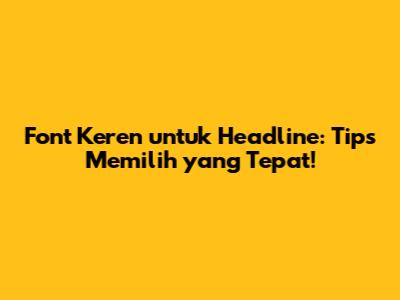
- Ukuran font: Pastikan ukuran font cukup besar agar mudah dibaca, terutama di layar kecil seperti smartphone. Ukuran font minimal untuk headline biasanya sekitar 24pt.
- Spasi antar huruf dan baris: Spasi yang cukup akan membuat huruf dan baris tidak terlalu berdekatan, sehingga lebih mudah dibaca. Hindari menggunakan spasi yang terlalu rapat atau terlalu lebar.
- Kontras warna: Pastikan ada kontras yang cukup antara warna font dan background. Hindari menggunakan warna yang terlalu mirip atau terlalu terang, karena bisa membuat mata lelah.
- Jenis font: Pilih jenis font yang memiliki desain karakter yang jelas dan mudah dikenali. Hindari menggunakan font yang terlalu rumit atau terlalu banyak ornamen.
- Kontras: Pilih font yang memiliki kontras yang cukup satu sama lain. Misalnya, kamu bisa mengombinasikan font serif untuk headline dengan font sans-serif untuk body text, atau sebaliknya.
- Hierarki: Gunakan font yang lebih tebal atau lebih besar untuk headline, dan font yang lebih tipis atau lebih kecil untuk body text. Ini akan membantu menciptakan hierarki visual yang jelas dan memudahkan pembaca untuk membedakan antara headline dan isi artikel.
- Kesesuaian: Pastikan font yang kamu pilih memiliki gaya dan tone yang serupa. Hindari mengombinasikan font yang terlalu berbeda, karena bisa terlihat aneh dan tidak profesional.
- Serif: Times New Roman, Georgia, Garamond, Didot
- Sans-serif: Arial, Helvetica, Open Sans, Roboto, Lato, Montserrat, Bebas Neue
- Display: Impact, Anton, Oswald, Playfair Display, Lobster
- Gunakan keyword di headline: Ini akan membantu meningkatkan SEO dan membuat headline-mu lebih relevan dengan pencarian pengguna.
- Buat headline yang menarik dan provokatif: Headline yang membangkitkan rasa ingin tahu akan membuat orang lebih tertarik untuk membaca kontenmu.
- Uji coba berbagai headline: Coba buat beberapa versi headline yang berbeda, lalu lihat mana yang paling efektif menarik perhatian pembaca.
Memilih font yang cocok untuk headline itu krusial, guys! Headline adalah wajah dari kontenmu, kesan pertama yang menentukan apakah orang tertarik untuk membaca lebih lanjut atau langsung scroll lewat. Bayangin deh, udah capek-capek bikin artikel super keren, tapi headlinenya pakai font yang bland dan nggak menarik? Sayang banget, kan! Nah, di artikel ini, kita bakal kupas tuntas gimana caranya memilih font yang bikin headline-mu stand out dan sukses mencuri perhatian.
Mengapa Pemilihan Font Headline itu Penting?
Font bukan sekadar hiasan, guys. Lebih dari itu, font adalah voice visual dari brand dan kontenmu. Pemilihan font yang cocok untuk headline bisa memengaruhi persepsi pembaca tentang kredibilitas, profesionalisme, dan bahkan emosi yang ingin kamu sampaikan. Bayangin, headline berita keuangan pakai font Comic Sans? Nggak banget, kan! Sebaliknya, headline artikel tentang desain grafis dengan font futuristik dan edgy bisa langsung menarik perhatian para desainer.
Selain itu, font yang cocok untuk headline juga berperan penting dalam readability atau keterbacaan. Headline yang mudah dibaca akan membuat pembaca lebih cepat memahami inti dari kontenmu. Ini penting banget di era digital yang serba cepat ini, di mana orang cenderung hanya scan informasi sebelum memutuskan untuk membaca lebih detail. Kalau headlinenya aja udah bikin mata lelah, bisa-bisa mereka langsung kabur!
Nggak cuma itu, font yang cocok untuk headline juga membantu membangun brand recognition. Dengan menggunakan font yang konsisten untuk headline di semua platform, kamu bisa menciptakan identitas visual yang kuat dan mudah diingat oleh audiensmu. Jadi, setiap kali mereka lihat font itu, mereka langsung ingat sama brand atau kontenmu. Keren, kan?
Memilih font yang tepat adalah investasi untuk kesuksesan kontenmu. Jangan anggap remeh hal ini, ya! Dengan pemilihan font yang cermat, kamu bisa meningkatkan engagement, membangun brand awareness, dan pada akhirnya, mencapai tujuan kontenmu.
Faktor-Faktor yang Perlu Dipertimbangkan dalam Memilih Font Headline
Oke, sekarang kita masuk ke bagian yang lebih teknis, yaitu faktor-faktor yang perlu kamu pertimbangkan saat memilih font yang cocok untuk headline. Jangan khawatir, nggak serumit yang kamu bayangkan kok!
1. Tujuan dan Target Audiens
Sebelum memilih font, kamu harus tahu dulu apa tujuan dari headline-mu dan siapa target audiensmu. Apakah kamu ingin menyampaikan informasi yang serius dan formal, atau justru ingin mengajak pembaca untuk bersantai dan menikmati konten yang ringan? Apakah target audiensmu adalah profesional muda yang tech-savvy, atau ibu-ibu rumah tangga yang mencari tips praktis? Jawaban dari pertanyaan-pertanyaan ini akan sangat memengaruhi pilihan fontmu.
Misalnya, kalau kamu menulis artikel tentang investasi saham untuk pemula, kamu mungkin ingin menggunakan font yang clean, profesional, dan mudah dibaca, seperti Arial, Helvetica, atau Open Sans. Font-font ini memberikan kesan kredibel dan terpercaya, yang penting banget dalam dunia keuangan. Sebaliknya, kalau kamu menulis artikel tentang fashion trends untuk remaja, kamu bisa lebih berani bereksperimen dengan font yang lebih stylish, playful, dan trendy, seperti Bebas Neue, Montserrat, atau Raleway.
Ingat, font adalah alat untuk berkomunikasi. Pilihlah font yang paling efektif untuk menyampaikan pesanmu kepada target audiensmu.
2. Gaya dan Tone Konten
Selain tujuan dan target audiens, kamu juga perlu mempertimbangkan gaya dan tone kontenmu. Apakah kontenmu bersifat formal atau informal? Serius atau lucu? Klasik atau modern? Pilihan fontmu harus selaras dengan gaya dan tone kontenmu.
Misalnya, kalau kamu menulis artikel tentang sejarah kuno, kamu mungkin ingin menggunakan font yang klasik dan elegan, seperti Times New Roman, Garamond, atau Didot. Font-font ini memberikan kesan vintage dan berwibawa, yang cocok banget untuk topik sejarah. Sebaliknya, kalau kamu menulis artikel tentang startup teknologi, kamu bisa menggunakan font yang modern dan futuristik, seperti Roboto, Lato, atau SF Pro Display.
Konsistensi adalah kunci. Pastikan font yang kamu pilih konsisten dengan gaya dan tone kontenmu di seluruh platform. Ini akan membantu membangun identitas visual yang kuat dan mudah diingat.
3. Readability dan Legibility
Ini adalah faktor yang paling penting, guys! Font yang cocok untuk headline harus mudah dibaca (readability) dan mudah dikenali setiap karakternya (legibility). Percuma kalau fontnya keren banget, tapi susah dibaca, kan? Pembaca bisa frustrasi dan akhirnya malah nggak jadi baca kontenmu.
Untuk memastikan readability dan legibility yang baik, perhatikan hal-hal berikut:
Uji coba adalah segalanya. Coba cetak headline-mu dalam berbagai ukuran dan warna, lalu minta teman atau kolega untuk membacanya. Perhatikan apakah mereka kesulitan membaca atau mengenali huruf-hurufnya. Jika ya, berarti kamu perlu mencari font lain.
4. Ketersediaan dan Kompatibilitas
Pastikan font yang kamu pilih tersedia dan kompatibel di semua platform yang kamu gunakan, baik website, media sosial, maupun email. Beberapa font mungkin hanya tersedia untuk penggunaan komersial, jadi pastikan kamu memiliki lisensi yang sesuai. Selain itu, beberapa font mungkin tidak didukung oleh browser atau sistem operasi tertentu, sehingga bisa tampil berbeda atau bahkan tidak tampil sama sekali di perangkat yang berbeda.
Untuk menghindari masalah ini, kamu bisa menggunakan font yang web-safe, yaitu font yang sudah terpasang secara default di sebagian besar sistem operasi, seperti Arial, Helvetica, Times New Roman, Georgia, dan Verdana. Atau, kamu bisa menggunakan layanan web font seperti Google Fonts atau Adobe Fonts, yang menyediakan ribuan font gratis dan berbayar yang bisa kamu gunakan di website-mu.
Periksa lisensi dengan cermat. Pastikan kamu memiliki hak untuk menggunakan font yang kamu pilih, terutama jika kamu menggunakannya untuk tujuan komersial.
5. Kombinasi Font
Seringkali, headline akan terlihat lebih menarik jika dikombinasikan dengan font lain untuk body text. Namun, memilih kombinasi font yang tepat bisa jadi tricky. Ada beberapa aturan dasar yang perlu kamu ikuti:
Jangan takut bereksperimen. Coba berbagai kombinasi font sampai kamu menemukan yang paling cocok untuk kontenmu. Kamu bisa menggunakan tools online seperti FontPair atau Canva Font Combinations untuk mendapatkan inspirasi.
Contoh Font yang Cocok untuk Headline
Nah, biar kamu nggak bingung, ini dia beberapa contoh font yang cocok untuk headline yang bisa kamu coba:
Ingat, ini hanyalah contoh. Kamu bisa bereksperimen dengan font lain yang sesuai dengan kebutuhan dan preferensimu.
Tips Tambahan
Kesimpulan
Memilih font yang cocok untuk headline memang membutuhkan sedikit riset dan eksperimen. Tapi, dengan mempertimbangkan faktor-faktor yang sudah kita bahas di atas, kamu pasti bisa menemukan font yang sempurna untuk kontenmu. Ingat, headline adalah wajah dari kontenmu, jadi jangan ragu untuk berinvestasi waktu dan tenaga dalam memilih font yang terbaik. Semoga artikel ini bermanfaat, guys! Selamat mencoba dan semoga sukses!